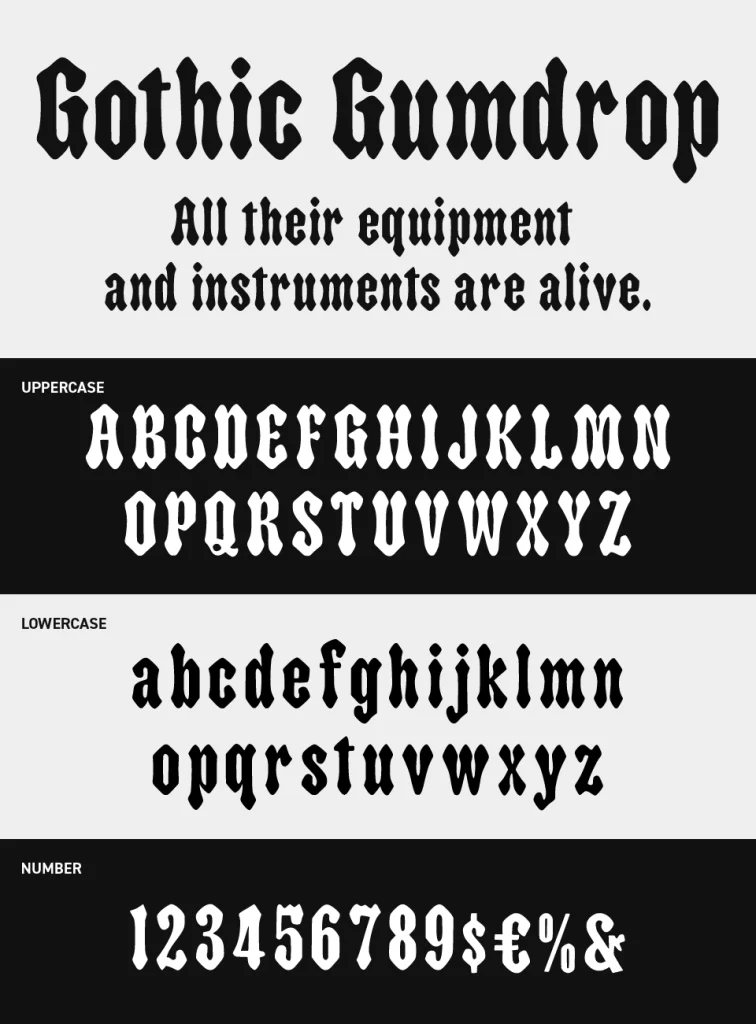
Gothic Gumdrop Font
Gothic Gumdropフォントは、伝統的なブラックレターの骨格を残しながら、丸みのある柔らかなフォルムにアレンジしたユニークなゴシックフォントです。
重厚でクラシカルな印象を持ちながら、レトロな風合いとどこかポップで親しみやすい独特のギャップが魅力です。
通常のゴシック書体よりも角がやわらかく処理されているため、威圧感を抑えつつ世界観をしっかり演出できます。ハロウィン、ダークポップ、海外カルチャー、個性的なアパレルデザインなど、少しクセのある表現をしたい場面にぴったりなフォントです。